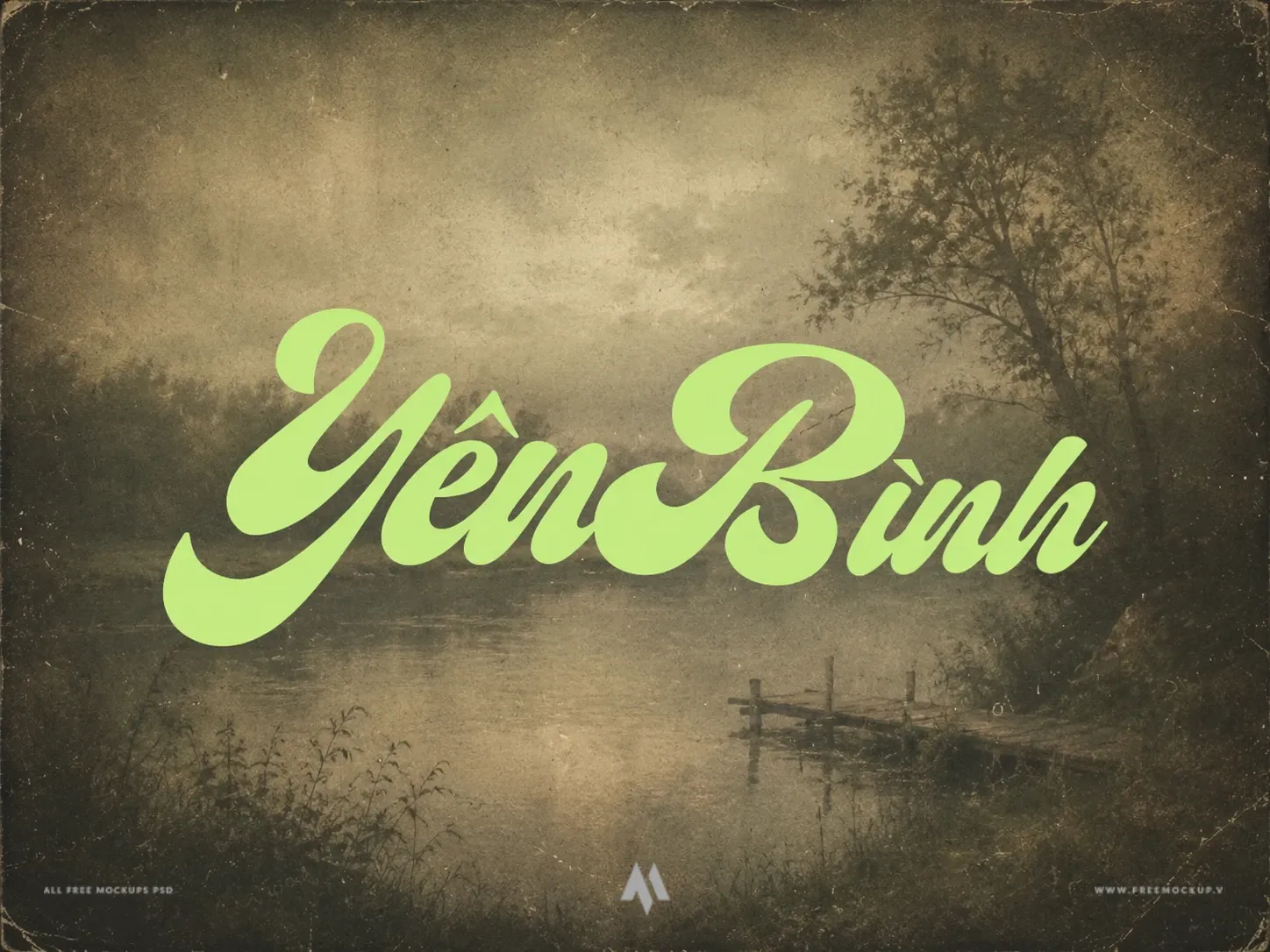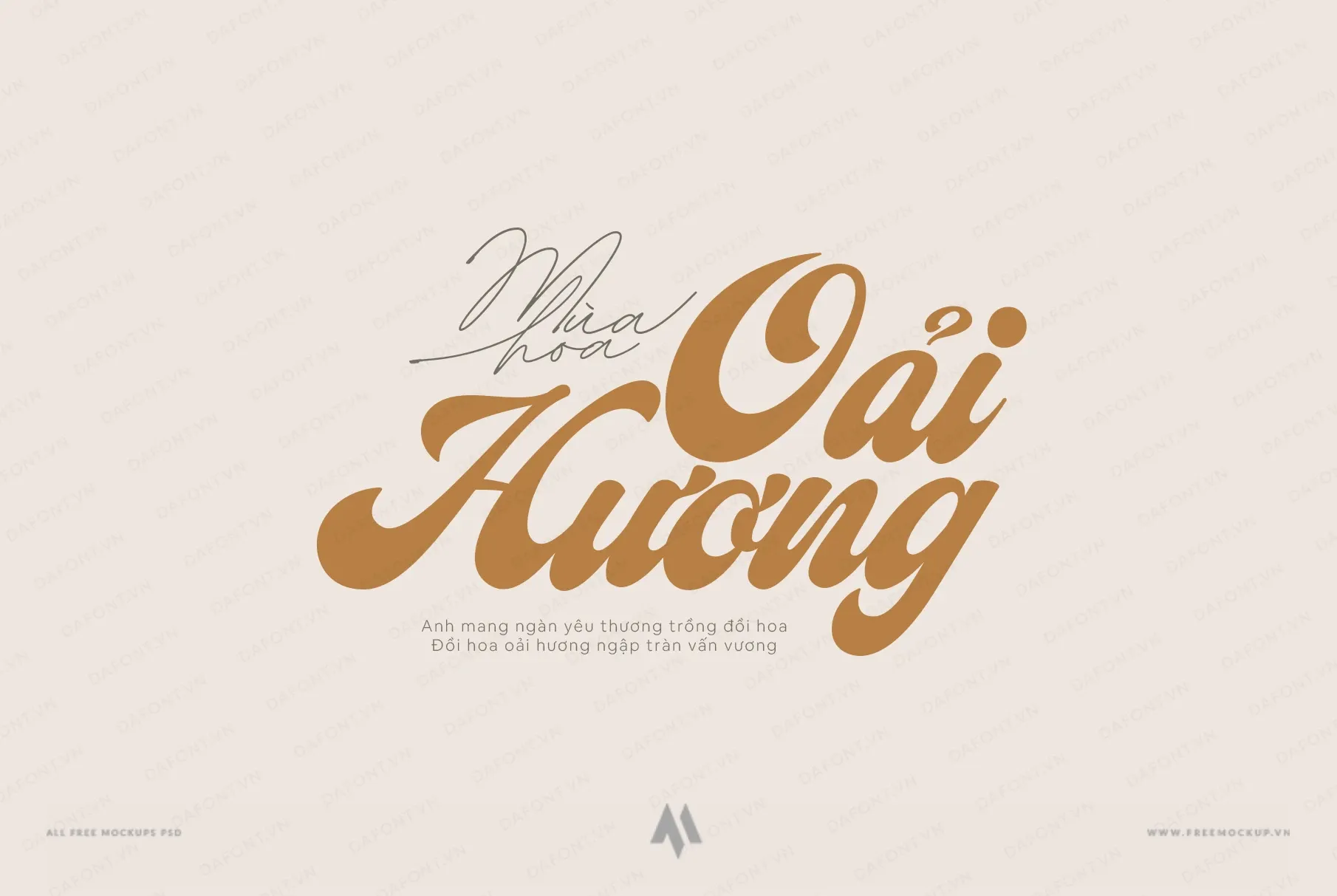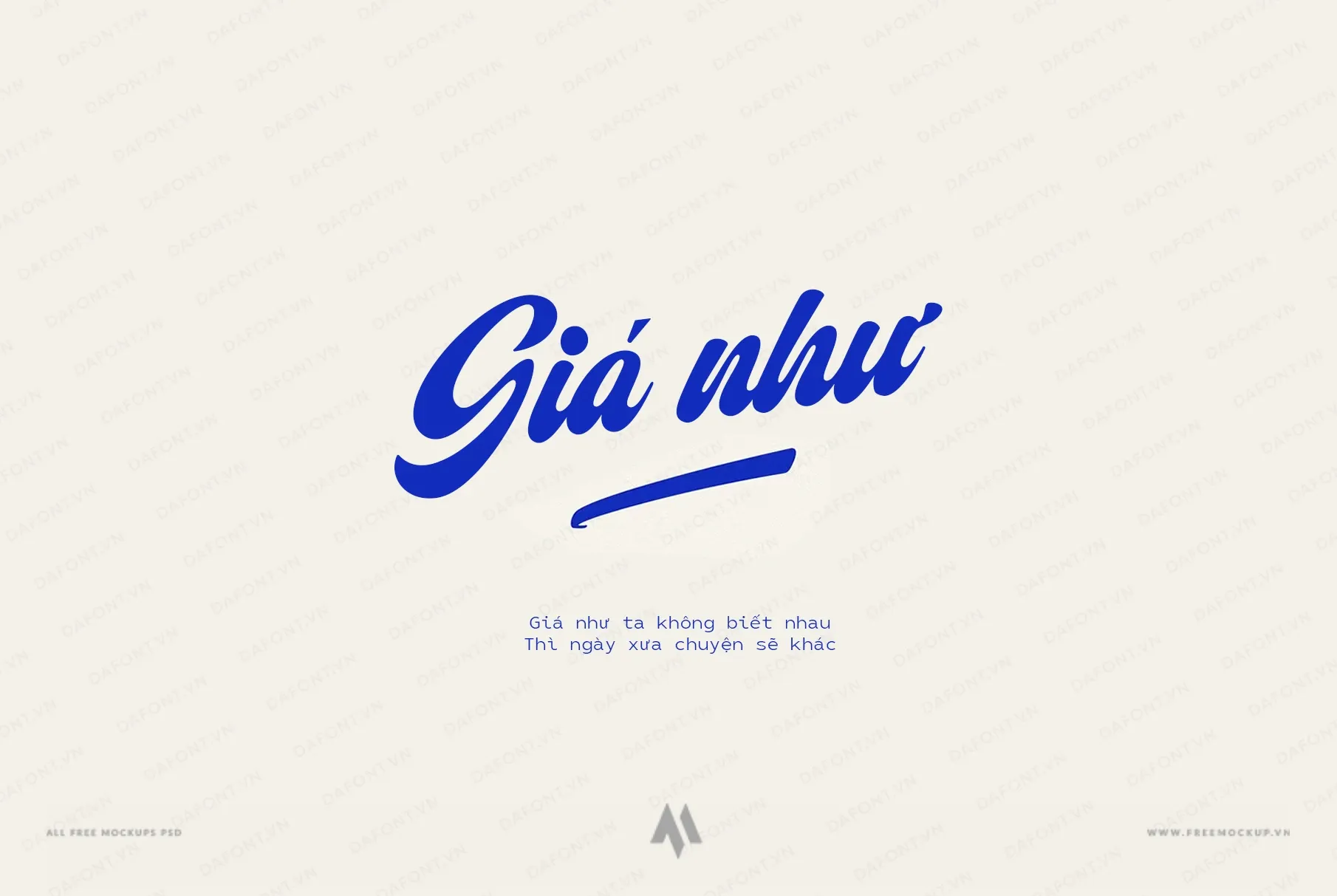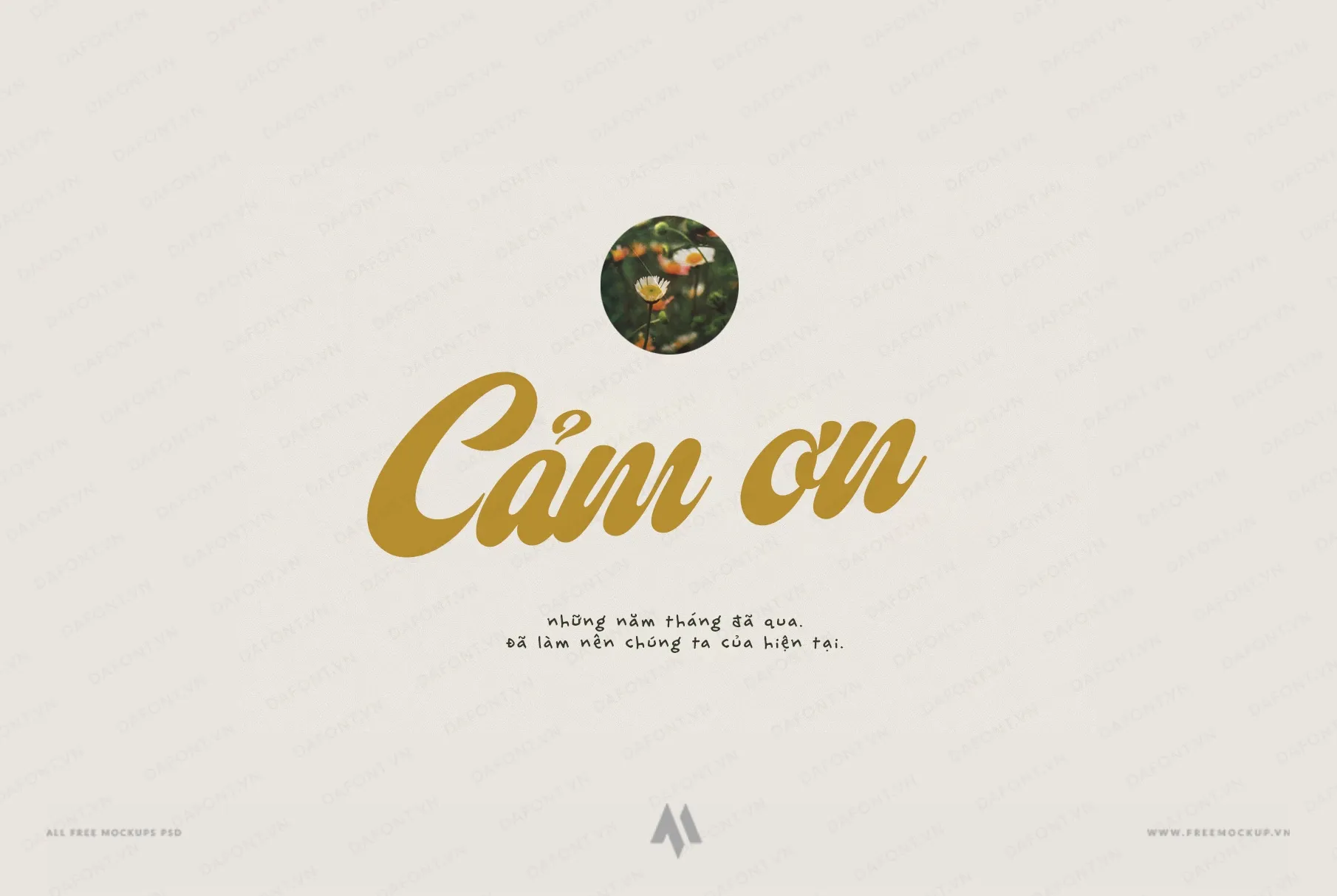
Font DFVN ED Piedmont là bộ font script đậm nét, giao thoa hoàn hảo giữa tinh thần retro thập niên 50 và hơi thở hiện đại. Được sáng tạo bởi Emyself Design và Việt hóa hoàn chỉnh, đây là lựa chọn lý tưởng cho các dự án đòi hỏi chất nghệ thuật cổ điển, sang trọng nhưng vẫn giữ trọn vẹn sự rõ ràng, dễ đọc.
Đặc điểm nổi bật của font DFVN ED Piedmont
- Đường nét mềm mại & Ligature linh hoạt: Hệ thống chữ hoa nổi bật với các nét cong uyển chuyển, kết hợp cùng các cặp ký tự dính (ligature) giúp câu chữ liền mạch, tự nhiên như chữ viết tay thủ công.
- Bộ ký tự toàn diện: Tích hợp đầy đủ chữ hoa, chữ thường, chữ số, biểu tượng đặc biệt cùng hỗ trợ đa ngôn ngữ và bảng mã tiếng Việt chuẩn.
- Tính ứng dụng cao: Tối ưu xuất sắc cho thiết kế logo, bộ nhận diện thương hiệu vintage, bao bì sản phẩm thủ công, poster sự kiện, nhãn mác thời trang và ấn phẩm marketing cao cấp.